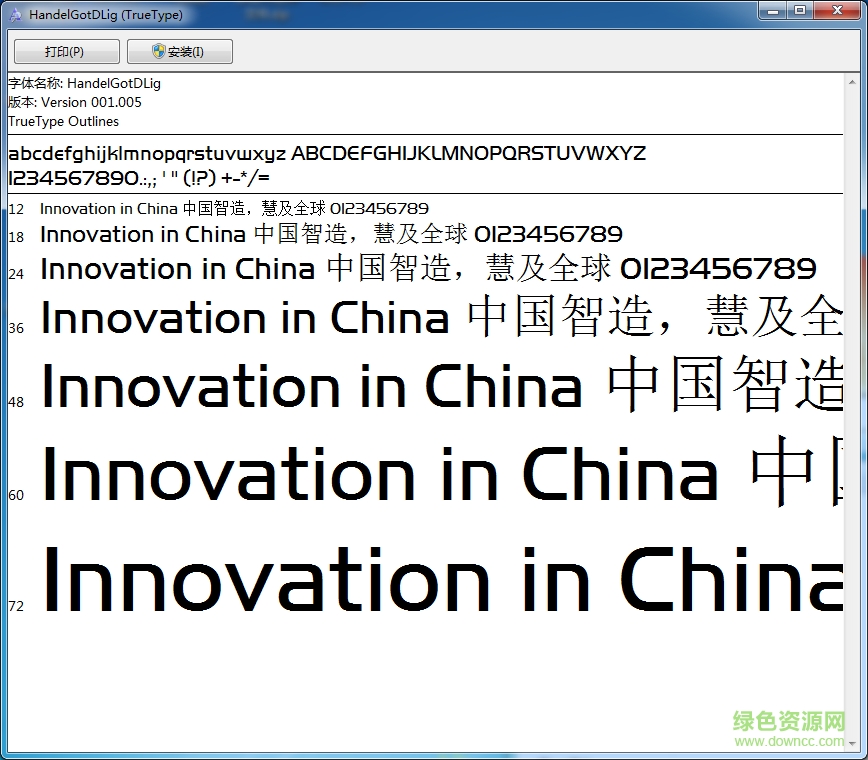
handelgotdlig是一款非常常用的英文字體,字體線條感十足,端正簡(jiǎn)單大方如行云流水一般,使用便捷時(shí)刻彰顯個(gè)人魅力??靵?lái)綠色資源網(wǎng)下載體驗(yàn)吧!
handelgotdlig字體是一款有著清新風(fēng)格的英文字體,大氣簡(jiǎn)潔的造型讓你的廣告設(shè)計(jì)、文字排榜更有特色,綠色資源網(wǎng)歡迎大家下載免費(fèi)版!